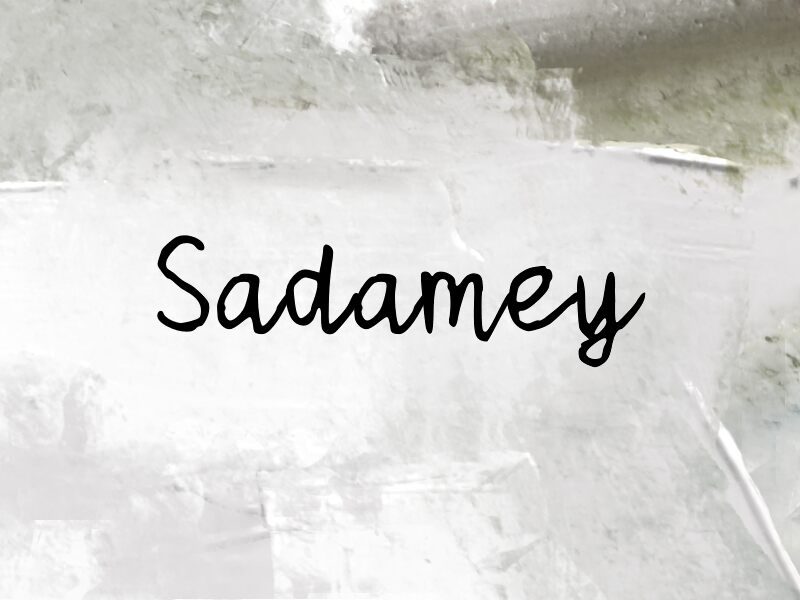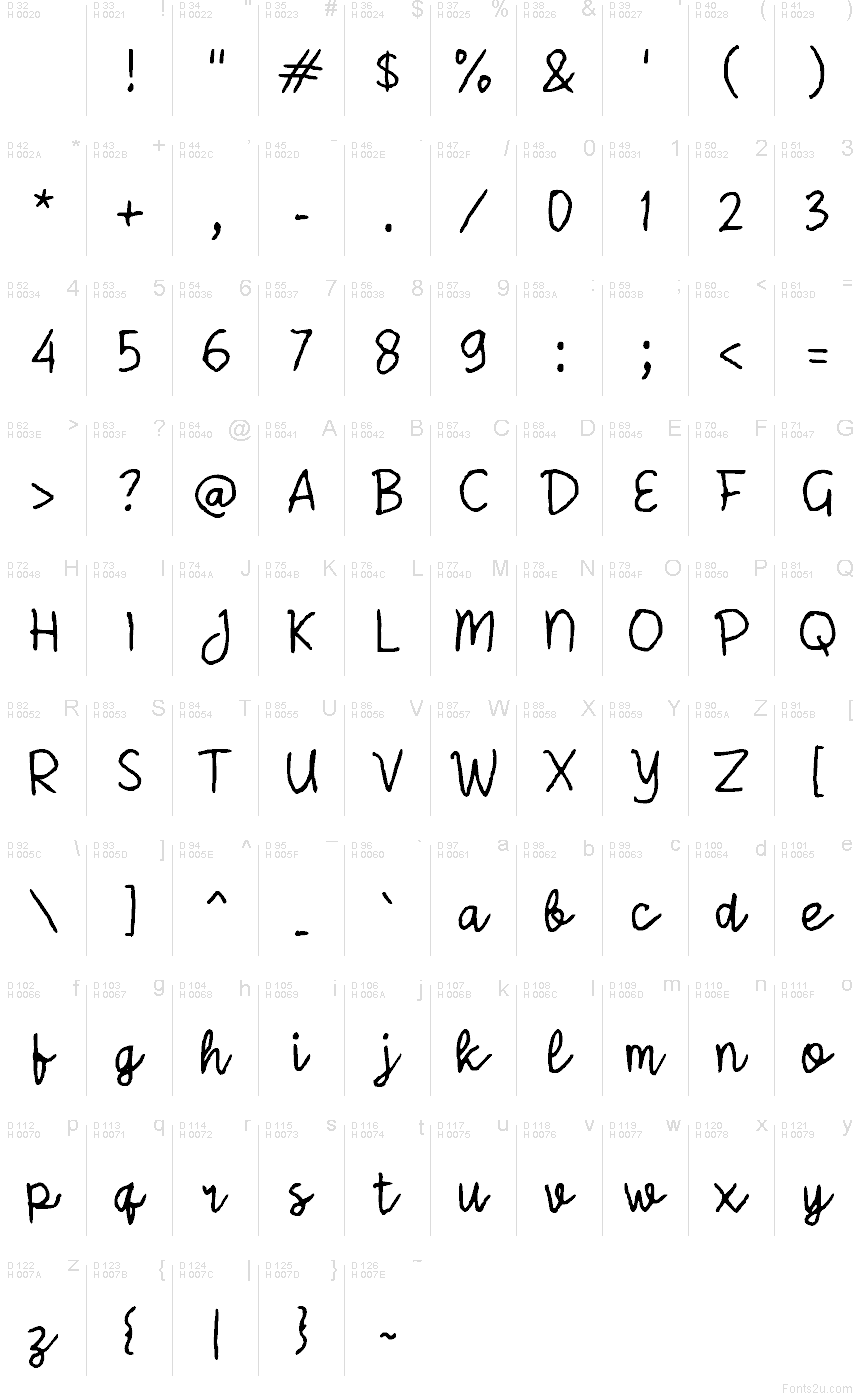
Sadamey
Sadamey da Wep é uma fonte manuscrita gratuita com um ritmo solto de pincel e traços arredondados que mantêm a escrita suave, sem parecer demasiado rigorosa. As formas alternam entre curvas altas e conexões rápidas, criando um fluxo leve e apressado, muito mais parecido com uma nota pessoal do que com uma caligrafia polida.
Esse movimento descontraído funciona perfeitamente em citações gráficas, menus de café, etiquetas de produtos, embalagens informais e posts nas redes sociais onde um toque humano é bem-vindo. Também é uma ótima escolha para cartões de felicitações e títulos de scrapbooking, especialmente quando você busca uma letra que pareça espontânea e acolhedora.